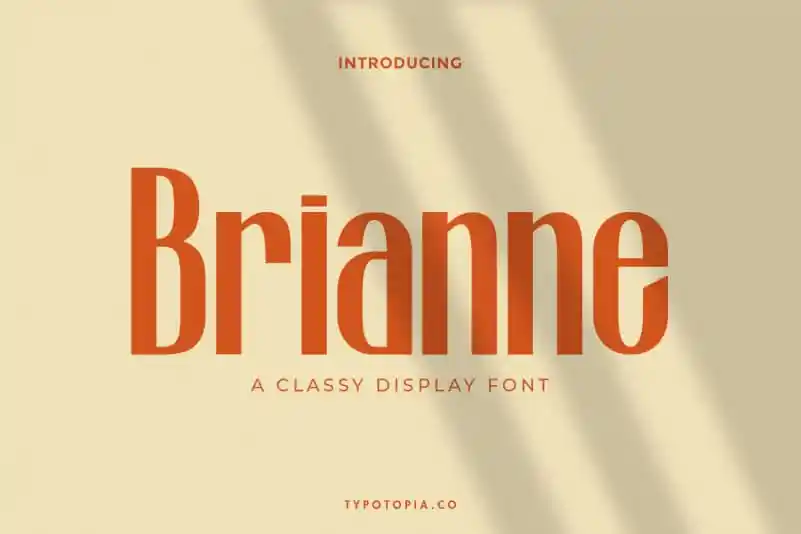
Introduzimos Brianne A Classy Display Font, uma elegante tipografia com estilo vintage semi-sérvio. Esta fonte foi criada para ser aplicada especialmente nos logos, panfletos, embalagens de papel higiênico, revistas, menus, livros, convites, cartões de visita, roupas, publicidade e cartão de visitas, entre outros usos decorativos. Seja para uma marca única ou um design mais sofisticado, Brianne A Classy Display Font traz um toque autêntico ao seu projeto. Ideal tanto para uso digital quanto em impressões profissionais, esta fonte é certamente a escolha perfeita se você está buscando algo que destaque suas criações de forma elegante e sofisticada.